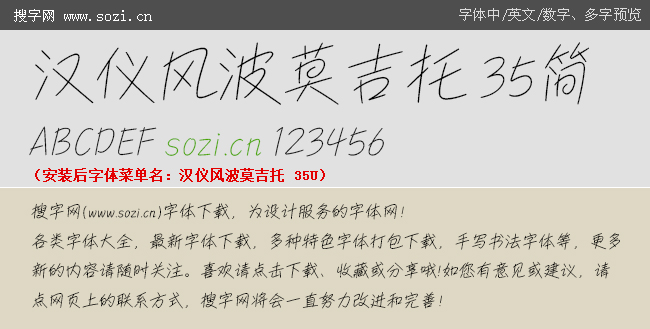
汉仪风波莫吉托 35简
搜字网给大家提供一款汉仪风波莫吉托 35简中文字体下载,汉仪风波莫吉托是一款具有独特艺术风格的字体,笔画流畅自然,富有动感和节奏感。线条的粗细变化丰富,能展现出独特的韵律。整体风格较为优雅,具有一定的文艺气息,同时又不失现代感。适用于画册设计、海报设计、包装设计等场合使用。(本字体为个人非商用版,如需要商用请联系汉仪公司购买版权)